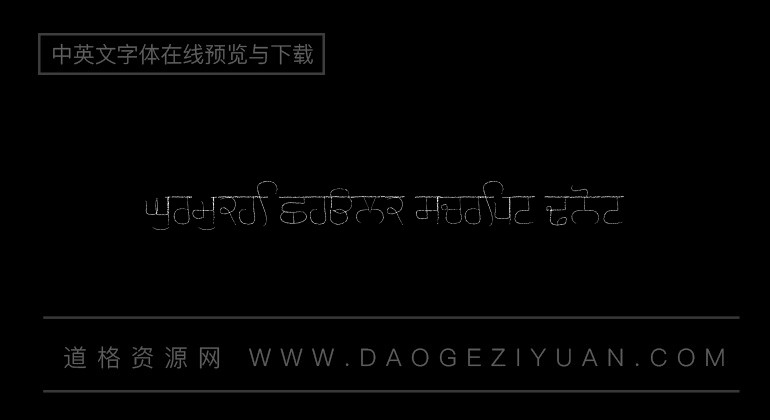
Gurmukhi Chalk script Font 是一种基于 Gurmukhi 脚本的手写粉笔字体。Gurmukhi 是一种印度次大陆使用的文字,它是锡克教的官方语言,也是旁遮普邦和哈里亚纳邦的官方语言之一。这种字体模仿了粉笔在黑板上书写的效果,具有非常自然和手写的感觉。 该字体非常适合用于设计传单、海报、印刷品等需要具有手写字体感觉的设计项目,特别是与锡克教文化和印度次大陆相关的设计。此外,该字体也可以用于装饰文本、标语、网站等其他类型的设计。 Gurmukhi Chalk script Font 字体提供了不同的字形和大小,可以根据不同的设计需求进行调整。它也可以与其他字体配合使用,以创建更具艺术感和个性化的设计效果。内容介绍
Gurmukhi Chalk script Font是一款非常不错的手写艺术字体,具有很好的视觉感,适合于文化类的宣传设计、商业类品牌的广告和产品包装设计以及个性化文字排版等较多场景。